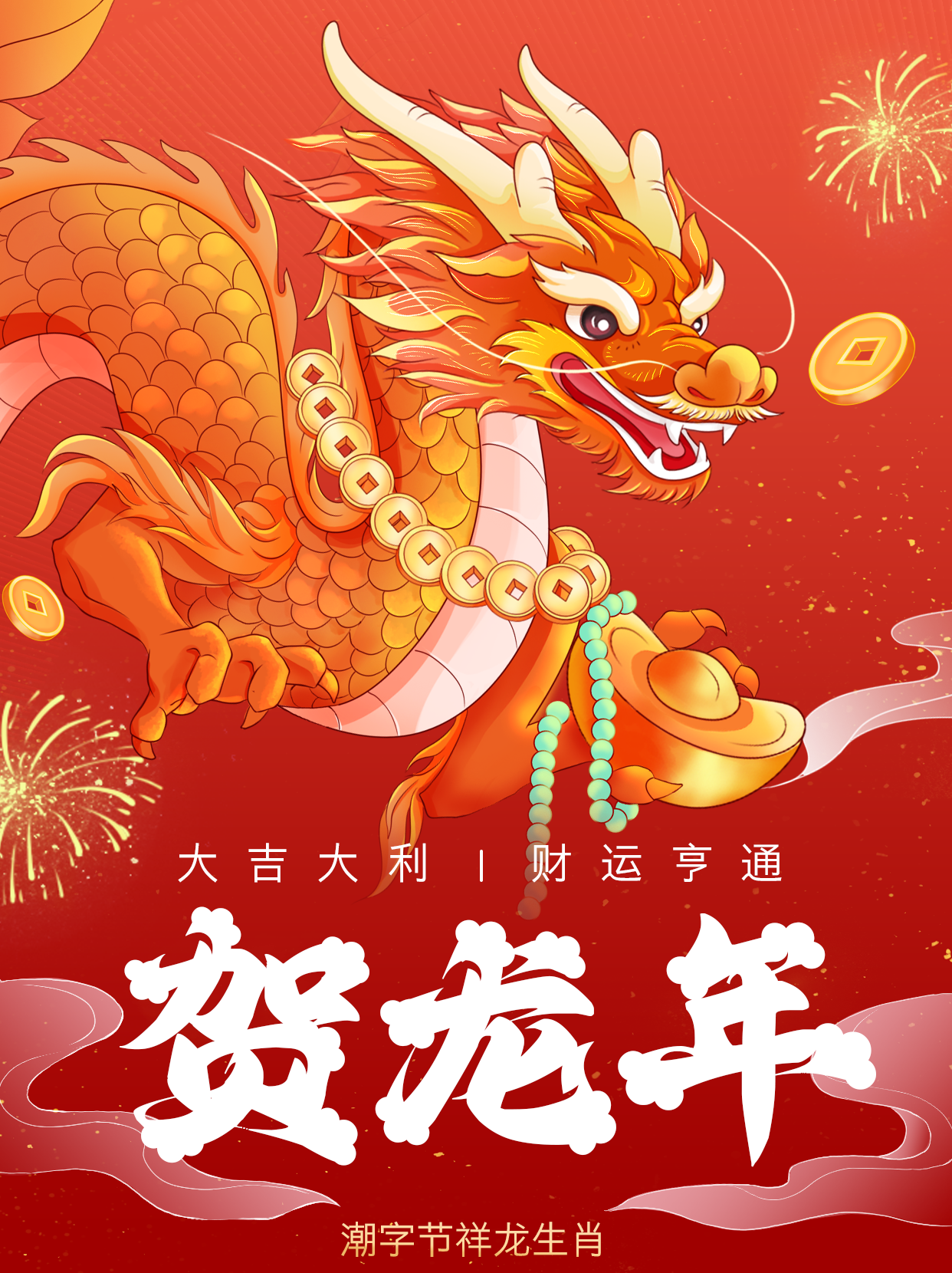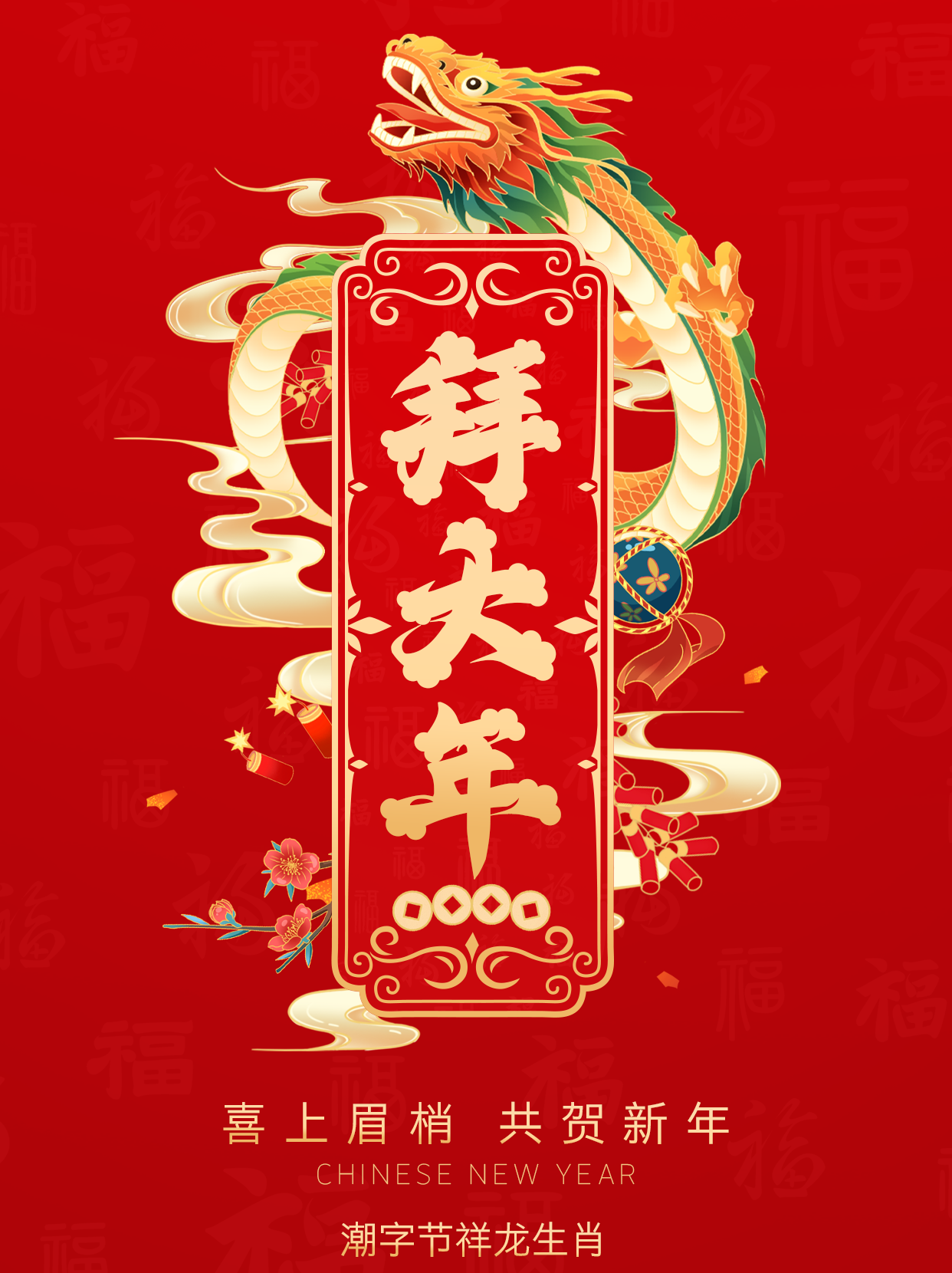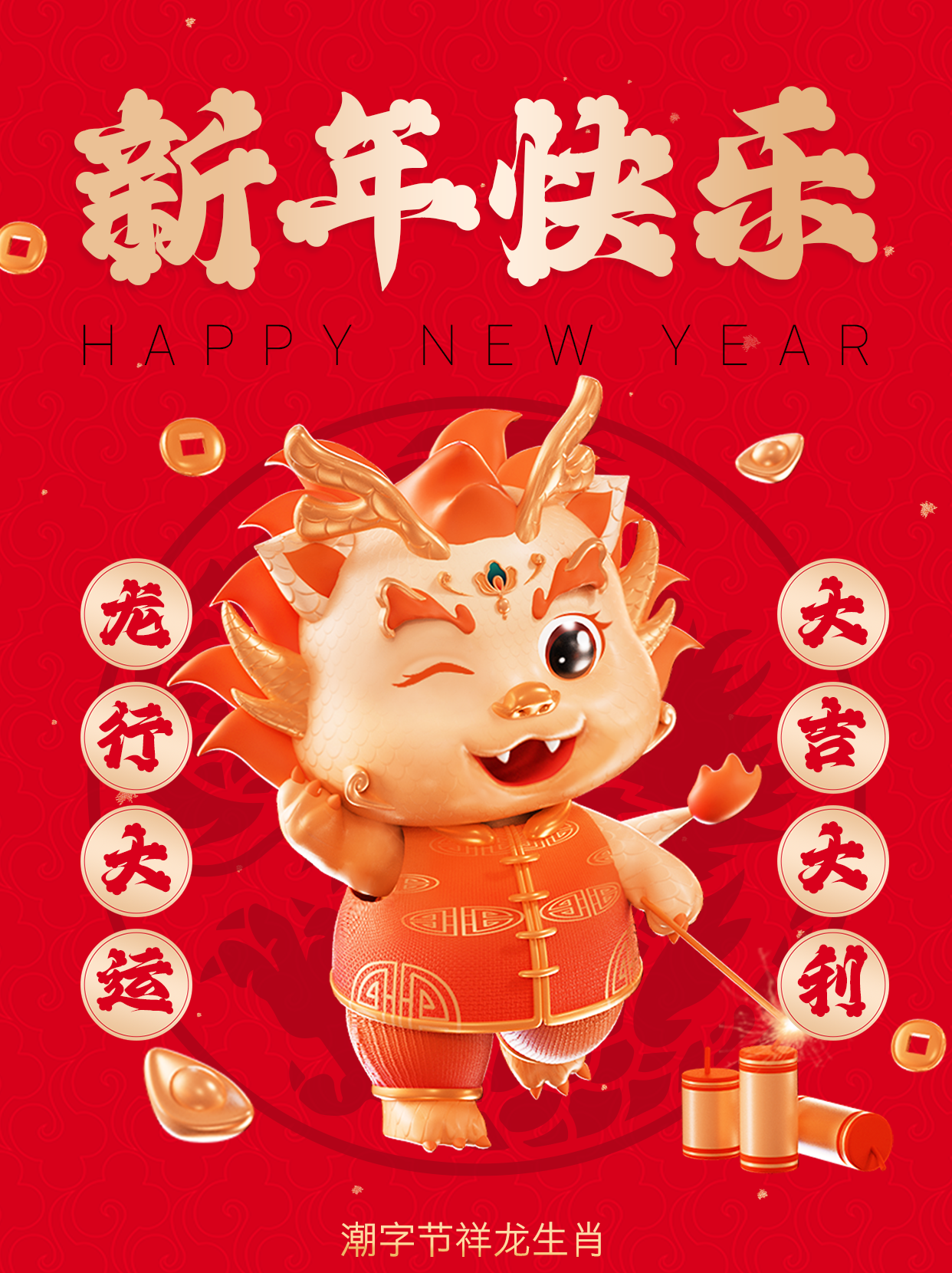
潮字节祥龙生肖是一款兼具传统书法和现代个性审美韵味的现代国潮手写体。其设计灵感来自古代经典装饰造型“祥龙献瑞”,以具象的笔画和抽象的结构呈现出龙举云兴的祥瑞造型。整体字形结构汲取了行草的流畅与楷书的稳健,从中凝练出具有游龙之姿的骨架,设计师在书写中不断尝试更加矫健的下笔,使得笔画妙墨飞舞,情至深处,主笔的起承转折间,因笔墨过于浓厚而晕染开,后期加工后形成了祥云般的造型,意想不到的将飞龙乘云之姿于字体之中活灵活现,整体造型的张力被加强的同时,也为文字增添了祥瑞之意。笔画转折处内部加入内切角,使其灵动似龙跃云津,赋予了祥龙生肖以生命力。这是一款将中国传统文化的精髓——祥云图案与生肖文化深度融合于书法艺术之中,创造出一种精湛独特且富有中国传统文化特色的字体。适用于品牌标识、品牌宣传、海报设计、产品包装等应用场景。